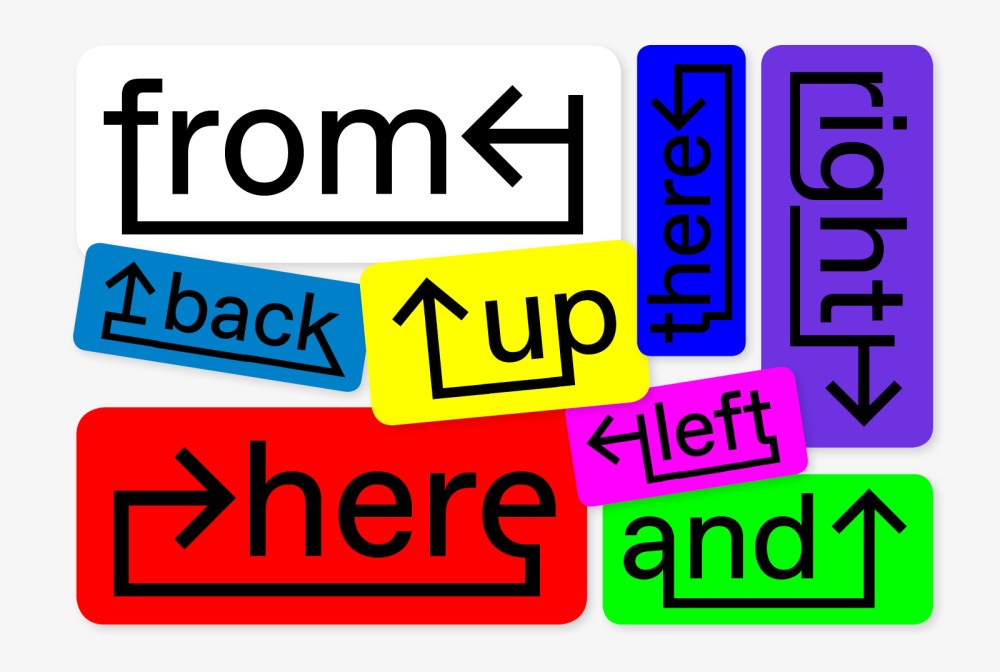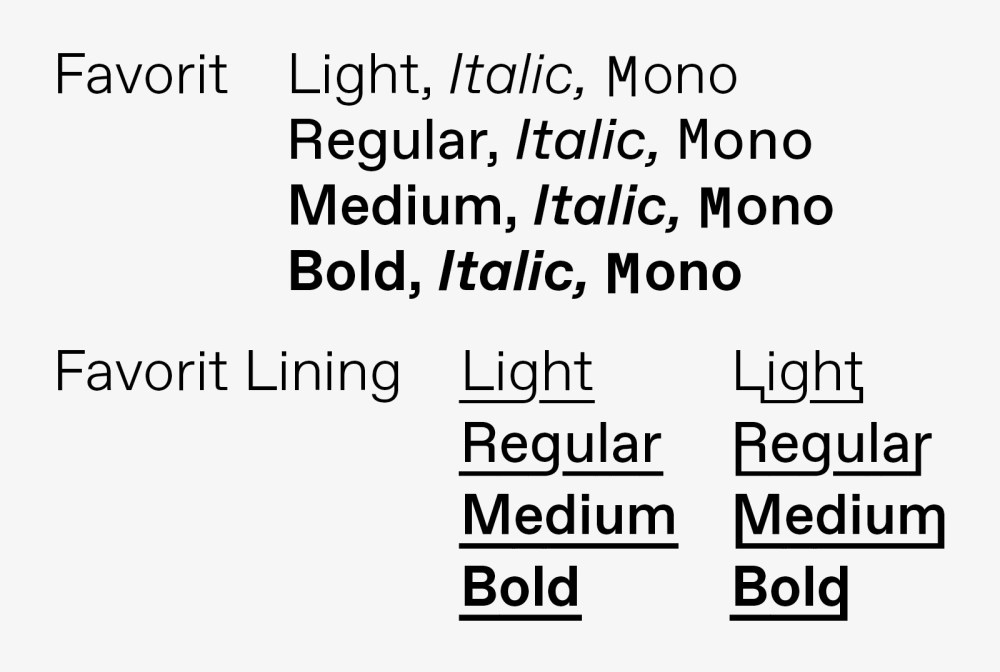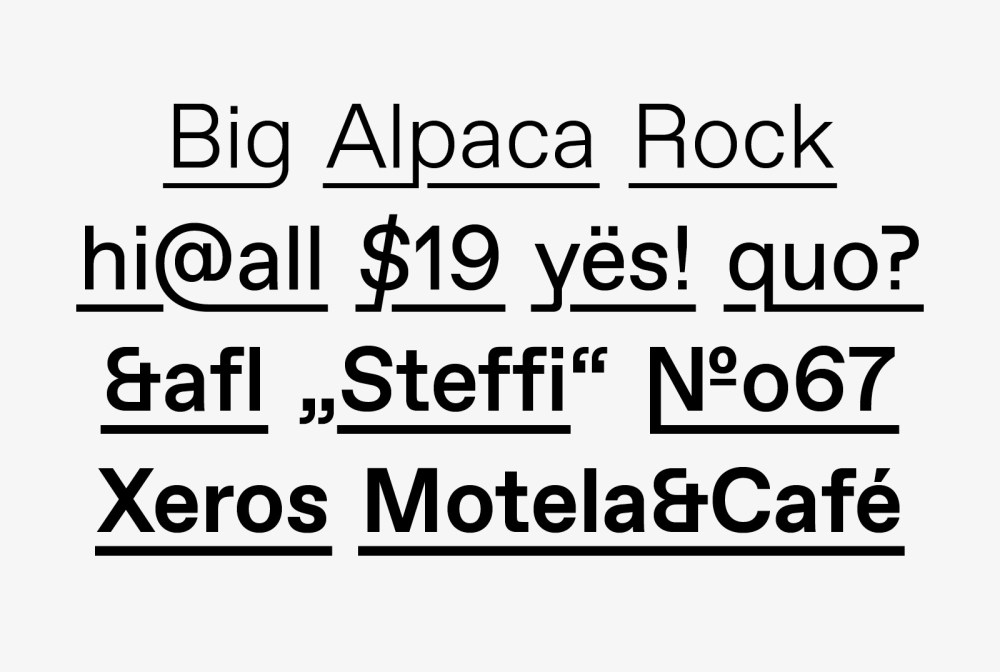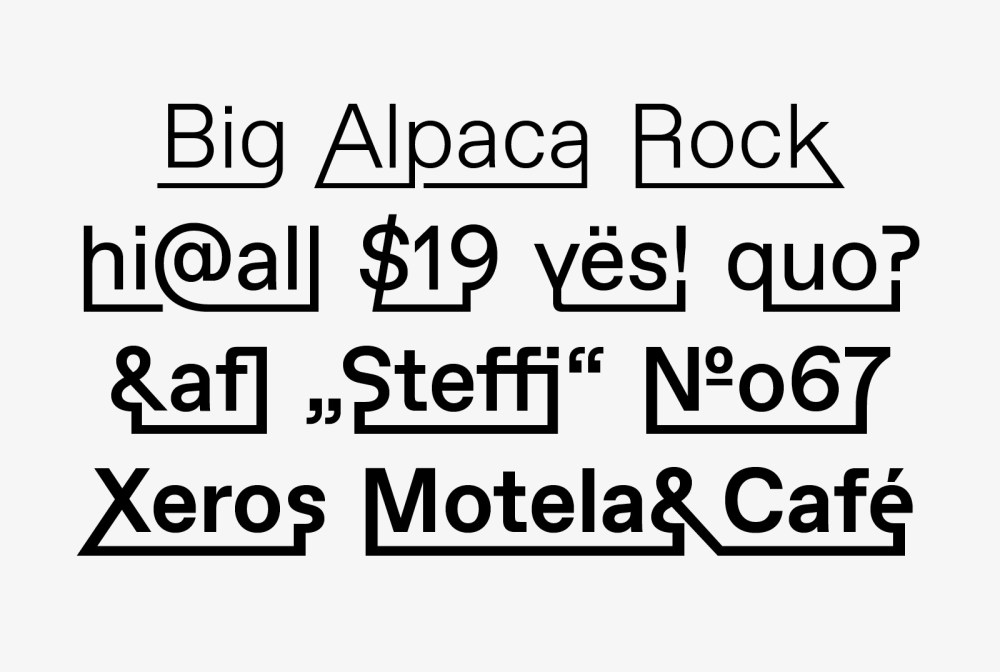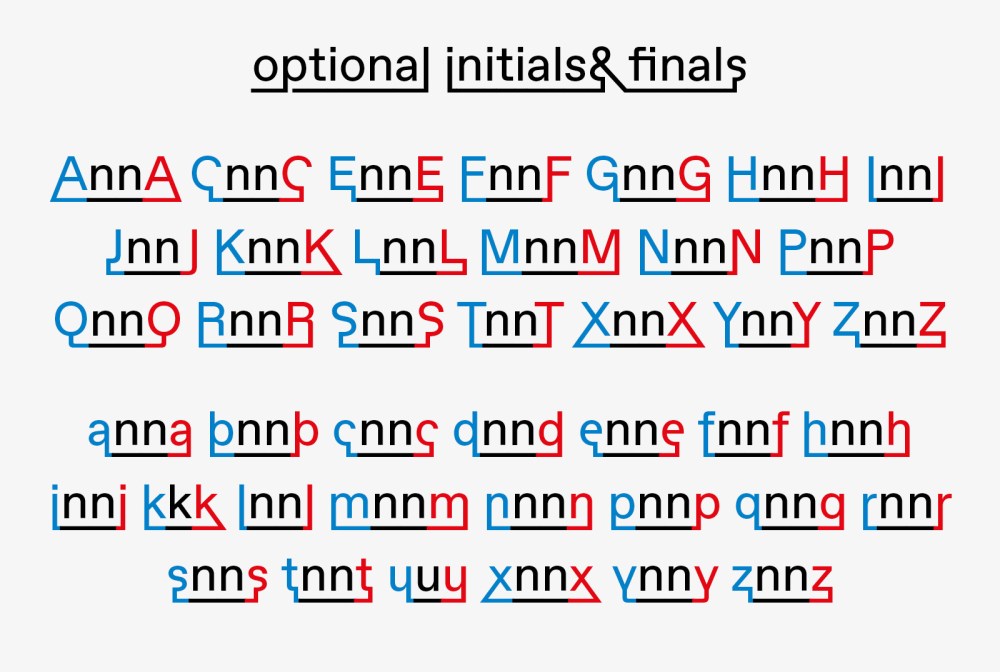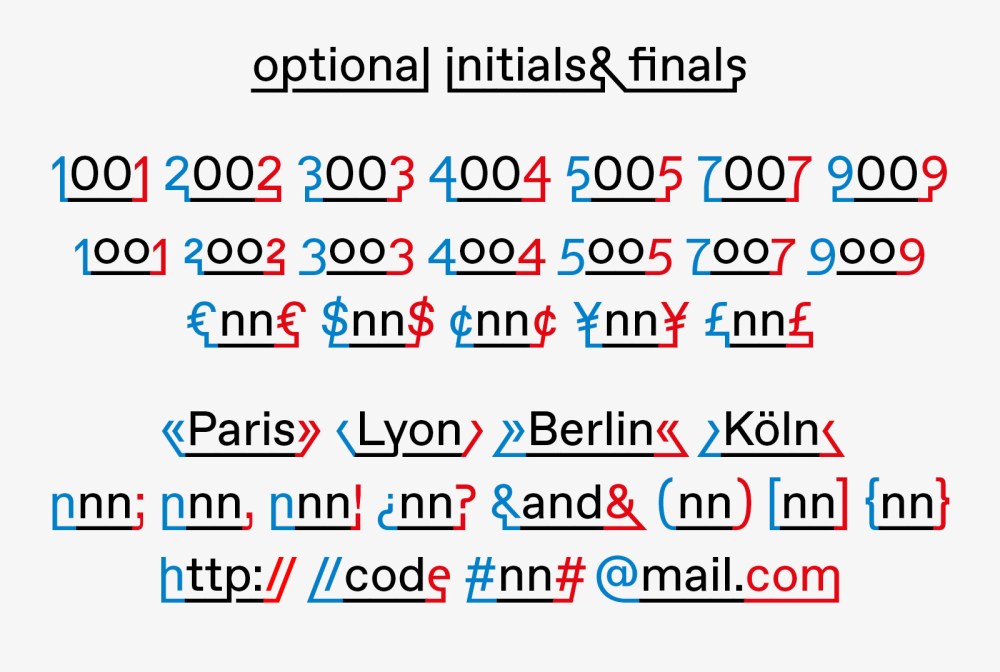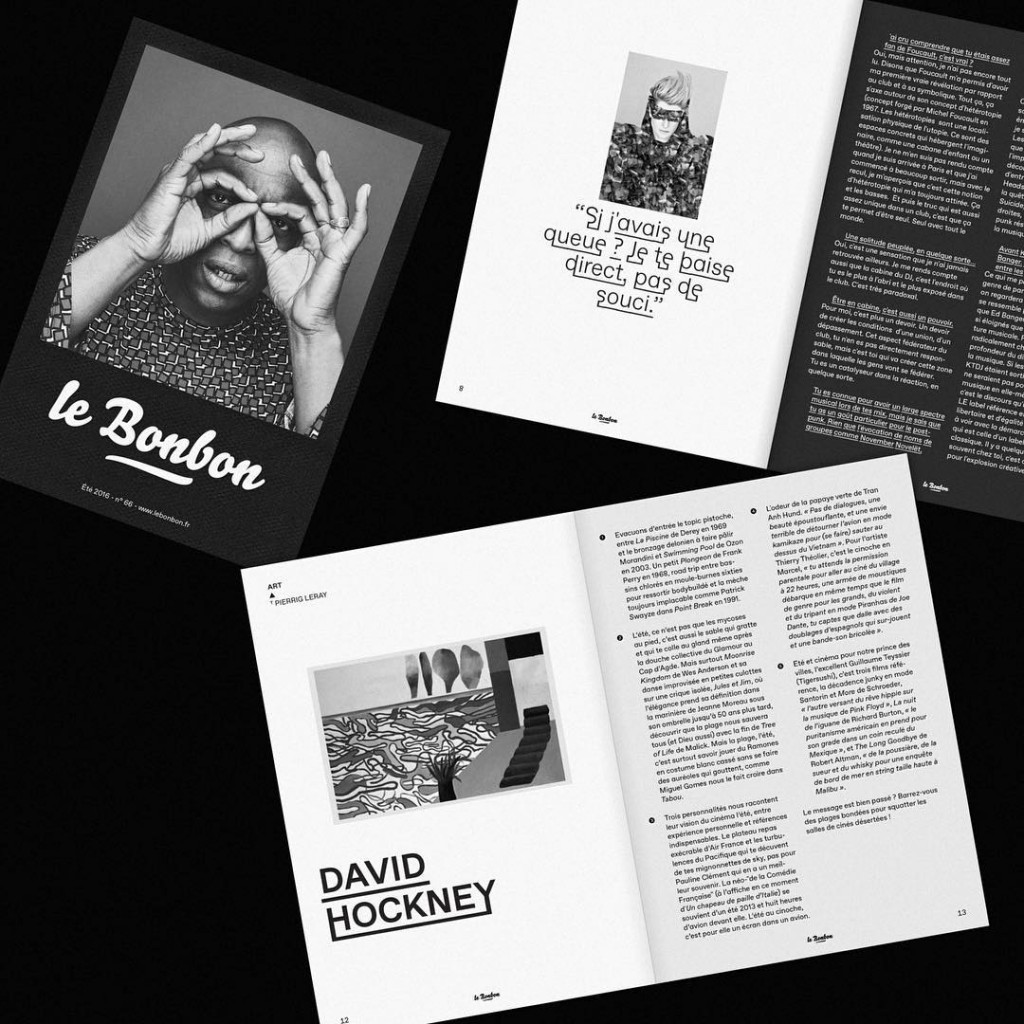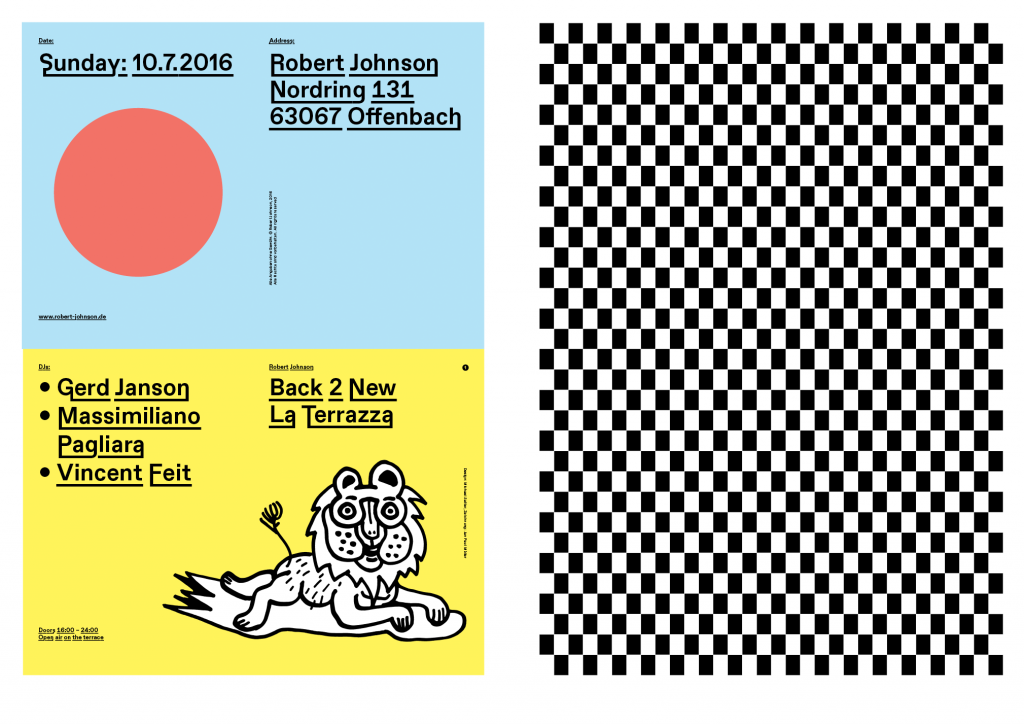
고유한 서체들(Unique Fonts) : Favorit Lining
본 연재는 국내외의 개인 혹은 기업에서 제작, 서비스하는 폰트 중 독특한 면을 가진 서체를 모아 소개한다. 서체 ‘파포리트 라이닝(Favorit Lining)’은 베를린과 스위스를 기반으로 활동하고 있는 그래픽 디자인 그룹 디나모(Dinamo)의 디자이너 요하네스 브라이어(Johannes Breyer)와 파비안 하르프(Fabian Harb)가 만들고 이모 슈나이더(Immo Schneider)의 도움을 받았다. 파포리트 라이닝(Favorit Lining)은 그들이 만든 기존의 Favorit 서체 패밀리 중 문자와 밑줄이 결합된 형태다.
고유한 서체들(Unique Fonts) : 4. Favorit Lining
라이닝은 이탤릭체와 같은 기능을 하는 다른 형태를 고안하면서 만들어졌다. 프로그램 상의 밑줄 기능을 이용하는 것이 아닌, 애초부터 서체에 최적화된 밑줄을 더해 이탤릭체보다 강한 인식이 가능하게끔 했다.
현재 크게 두 가지 형태로 나와 있다. 첫 번째 형태는 단순하게 문자 하단에 밑줄을 추가하면서 알파벳 g, j, q, p, y처럼 기준선 아래로 뻗어 있는 문자를 밑줄과 자연스럽게 잇는다.
두 번째 라이닝은 첫 번째 라이닝 보다 흥미로운 연결 방식을 가지고 있는데, 대문자 B, D, O, U, V와 소문자 w, v, o(막혀 있거나 획이 끝나는 지점이 상단을 향함)를 제외한 나머지 문자가 단어의 처음/마지막에 쓰이는 경우 문자와 밑줄이 연결되어 단어 하나가 독립적인 영역을 만들 수 있게 한다.